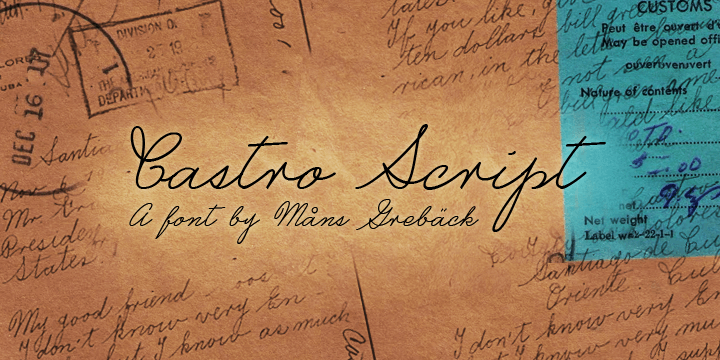
A fonte ‘Castro Script’ é uma criação sofisticada e encantadora criada pelo designer Hamilton. Inspirada na elegância dos scripts antigos, ela oferece uma experiência visual única para qualquer design que se encontre entre as folhas de letras delicadas e fluidas. Com suas curvas perfeitas e detalhes meticulosamente cuidados, ‘Castro Script’ é ideal para criar um texto atraente e impecável. Ideal tanto para aplicações comerciais quanto de uso pessoal, esta fonte não apenas adicionará uma camada especial de charme ao seu design, mas também permitirá que você transmita sua mensagem de forma ainda mais poderosa e memorável. Compreender os recursos e as possibilidades criativas disponíveis através desta fonte pode revolucionar o modo como você trabalha com texto. Seja para criar uma marca memorável ou apenas aprimorar seu design editorial, ‘Castro Script’ é uma escolha que definitivamente não decepcionará. Visite o site oficial de Mansgreback para explorá-la e fazer sua própria descoberta.